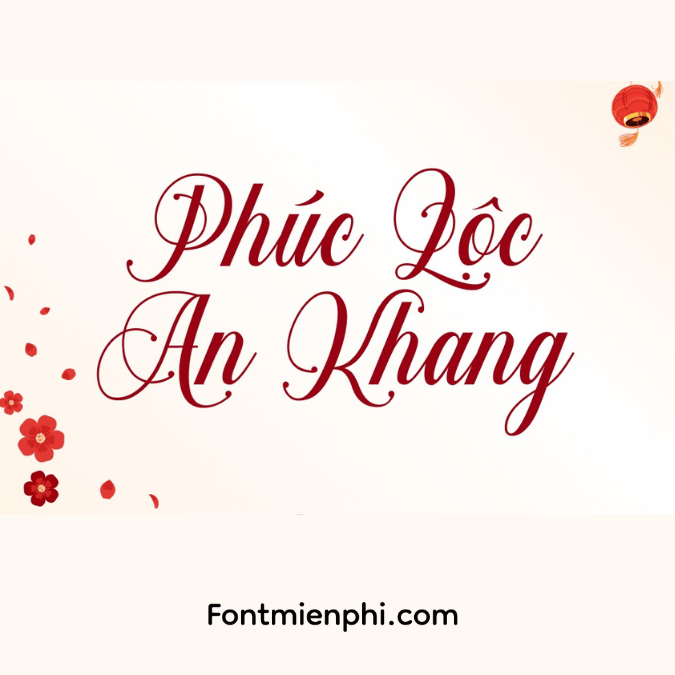
Font Việt hóa 1FTV VIP Chalisa Oktavia ,font tết
FONT VIỆT HÓA 1FTV VIP CHALISA OKTAVIA
“Nét chữ thanh lịch – Tinh thần hiện đại”
ĐẶC ĐIỂM NỔI BẬT
Phong cách Feminine Elegance: Nét chữ mềm mại với độ dày biến đổi tinh tế, phù hợp thiết kế nữ tính
Họa tiết hoa văn cách điệu: Điểm nhấn bằng các chi tiết hoa lá mảnh mai tại các điểm kết thúc nét
️ Chất calligraphy hiện đại: Kết hợp hài hòa giữa nét truyền thống và xu hướng thiết kế đương đại
Font Việt hóa 1FTV VIP Chalisa Oktavia ,font tết
• Regular (nét chuẩn)
• Swash (nét hoa văn phức tạp)
• Lined (hiệu ứng viền kép)
• Rough (chất liệu cọ vẽ)
“Chalisa Oktavia – Viết lên những câu chuyện dịu dàng”